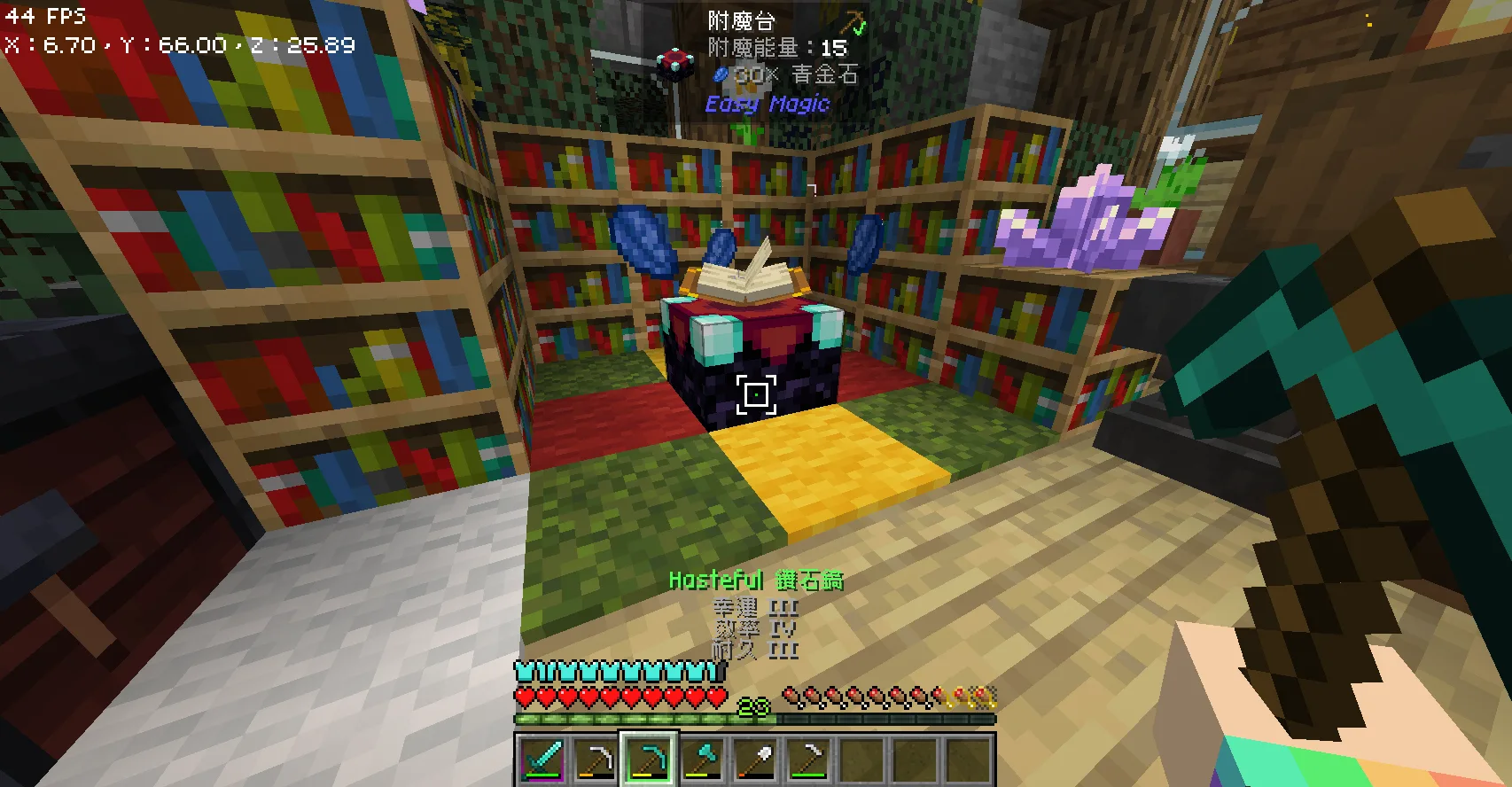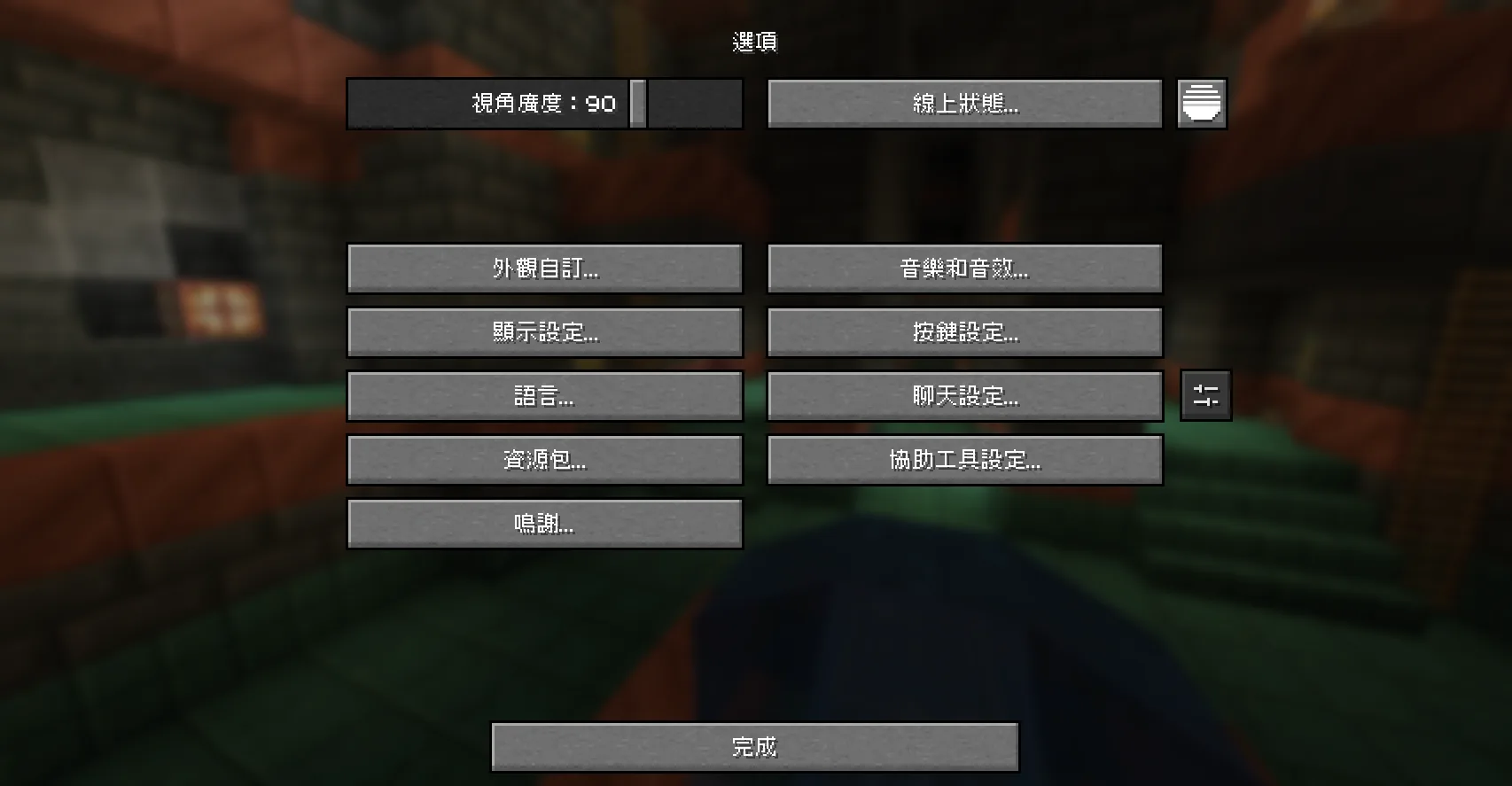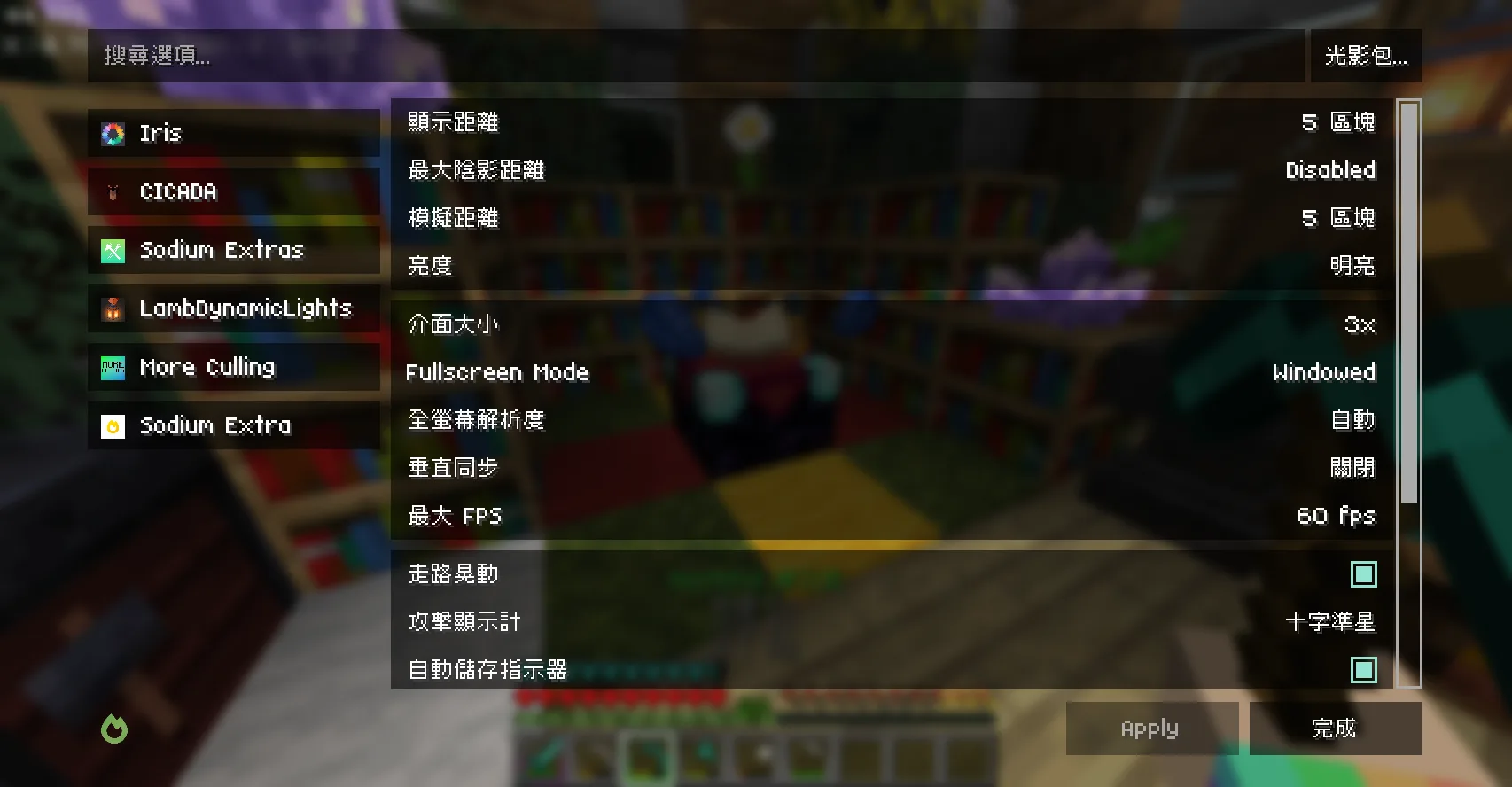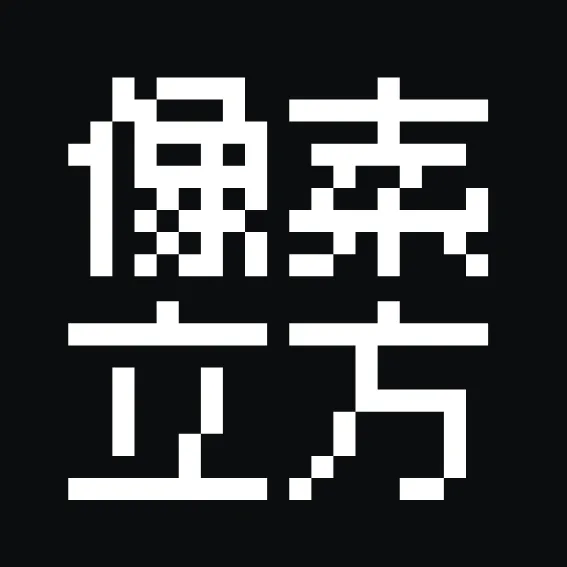
Pixel Font (chinese)
Этот ресурспак использует пиксельный шрифт Cubic 11 для китайских символов и Compact Font для английских, идеально сочетаясь со стилем ванильного шрифта Minecraft Seven.
Ресурспак применяет настоящий пиксельный шрифт Cubic 11 для отображения китайских символов и Compact Font для английских, обеспечивая чёткость и читаемость текста. Он идеально соответствует стилю ванильного шрифта Minecraft Seven, что повышает визуальную согласованность текста в игре. Это улучшает общее впечатление от игры, делая интерфейс более гармоничным и удобным для восприятия.